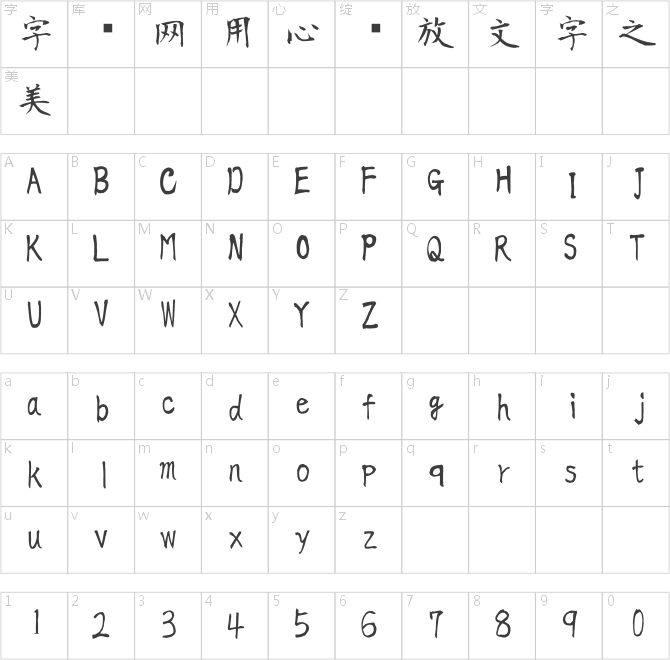
莫大毛笔体
莫大毛笔体介绍
字体介绍 莫大毛笔体是基于衡山毛笔体的开放原始码中文字型增加更多字重的字数的修改版字体。衡山毛笔字体是来自于日本书法家青柳衡山,目前字型内文字和符号字数在:14,321个。 与衡山毛笔体体有何不同? 1、增加了更多中文字体 莫大毛笔体补齐台湾教育部列出的4,808个常用字,在原本的衡山毛笔字体架构下,莫大毛笔字体增加(和修改)168个字。 2、增加了字体字重,现在总共5个字重 原本的衡山毛笔字体放在Regular字重裡,现在透过程序自动产生ExtraLight、Light、Medium、Bold 新的字重。Light字重是把原本的KouzanBrushFont微微调细一点点。在ExtraLight的字重裡,可能会因为笔划太细造成某些笔画消失。在Medium和Bold的字重裡,可能会因为笔划太粗造成某些笔画重叠难以识别,有粗体字的需求,可以先挑战使用Bold字重看看,如果发现效果不如预期,再改用Medium字重。 不能确定自动产生出来的字重裡每一个都是完整的字,毕尽程式会误判是常有的事情,所以不是在Regular字重裡的笔划可能会消失。 3、清除衡山毛笔字体裡空白的文字 衡山毛笔字体裡有很多空白的字, 会造成无法让系统自动用预设字体来补字,已清除空白的文字。 4、调整标点符号位置 衡山毛笔字体的全形标点符号针对日本做设计,调整为台湾常见的置中用法。半形的backslash,调整为非日本地区用法。 5、增加部分台湾口语出现的中文字和增加部份的粤语字 在原本的衡山毛笔字体架构下,莫大毛笔字体增加11字。感谢网友Luke Liu的贡献,在莫大毛笔字增加86个粤语字。 字体授权 授权出处:https://max-everyday.com/2020/03/bakudaifont/ 这款字体是依据SIL Open Font License 1.1授权协议,可以用于任何用途,包括免费商用。 开放字体许可证(OFL)是由SIL国际维护的。它试图在自由软件和字体设计社区的价值观之间达成妥协。它用于几乎所有开源字体项目,包括Adobe、Google和Mozilla。